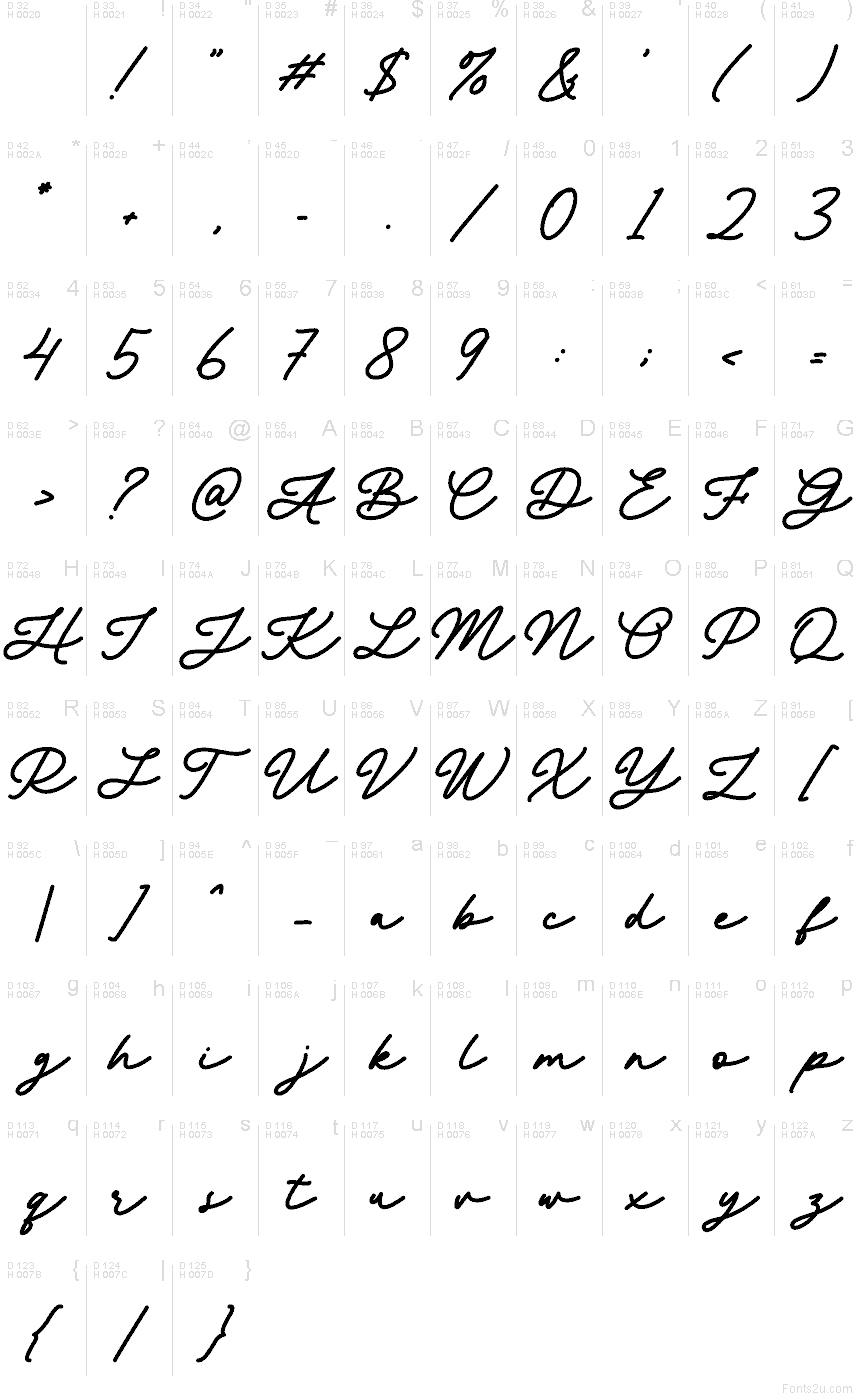
October Shine
October Shine, da RantauType, é uma fonte manuscrita gratuita caracterizada por traços longos e envolventes e um ritmo descontraído que remete mais a uma escrita natural do que a uma caligrafia formal. Seus laços amplos e o movimento horizontal alongado conferem às letras uma silhueta suave e leve, em vez de um aspecto caligráfico rígido.
Essa fluidez é ideal para embalagens de produtos, cardápios, branding de lojas, artes com frases ou títulos de convites onde o toque pessoal é essencial. Funciona particularmente bem em títulos curtos, já que as conexões estendidas e as curvas abertas emolduram o layout com elegância, sem parecerem excessivamente decoradas.